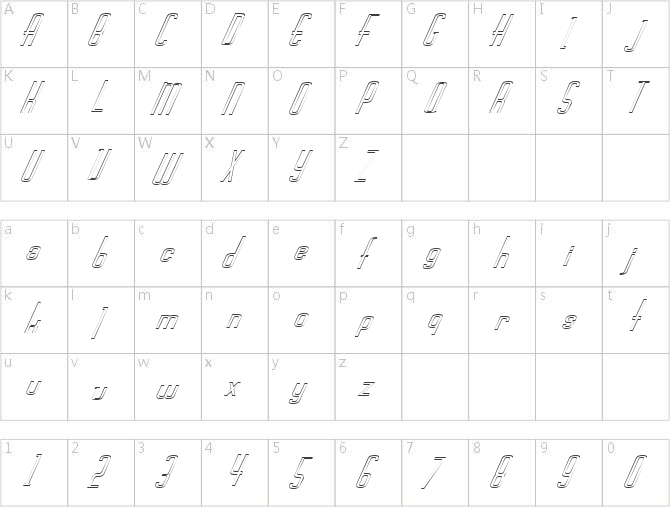
FZ BASIC 44 HOLLOW ITALIC
FZ BASIC 44 HOLLOW ITALIC介紹
FZ BASIC 44 HOLLOW ITALIC字體字庫是一款讓人賞心悅目、百看不厭的英文字體,適合各類廣告和產品包裝設計應用,字體大小0.07MB,格式為ttf字體,上傳用戶是xqy,作者/版權方為未知
FZ BASIC 44 HOLLOW ITALIC效果圖